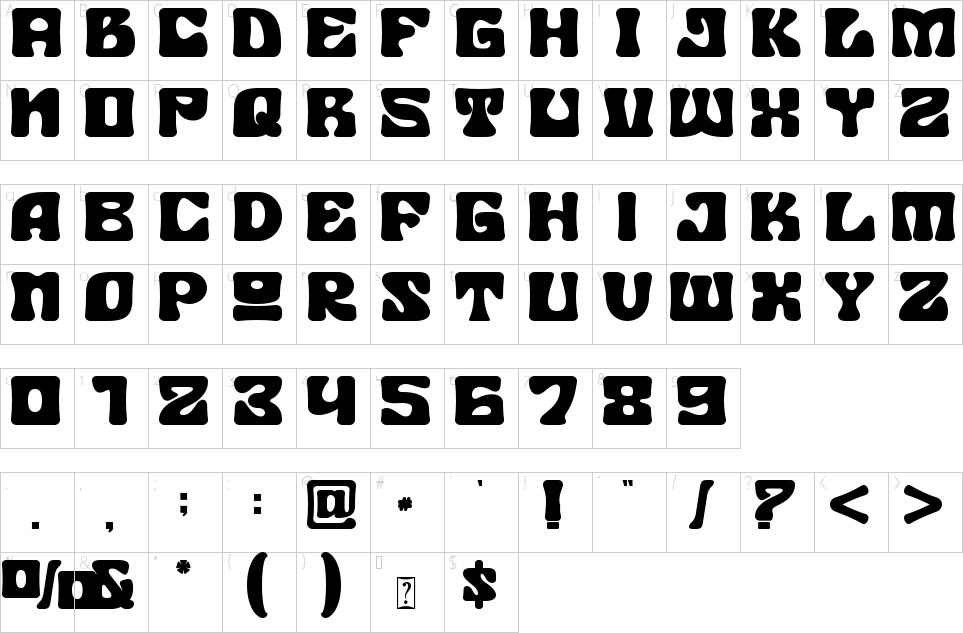
Descubra a sofisticação e a elegância do Allrion font, uma opção gratuita e elegante para seus projetos de design. Criada pelo Letterara Studio, Allrion oferece uma aparência moderna e envolvente que certamente se adequará perfeitamente para aplicações no Windows e Mac. Se você procura uma fonte clara, fácil de ler e que não comprometa a aparência do seu design, Allrion pode ser uma escolha ótima. Com um design cuidadosamente elaborado e uma ampla gama de opções de estilo, Allrion é uma fonte perfeita para designers buscando qualidade e simplicidade em cada letra. Com apenas 246 downloads, já provou sua eficácia e conveniência. Download agora e transforme seus projetos com Allrion.